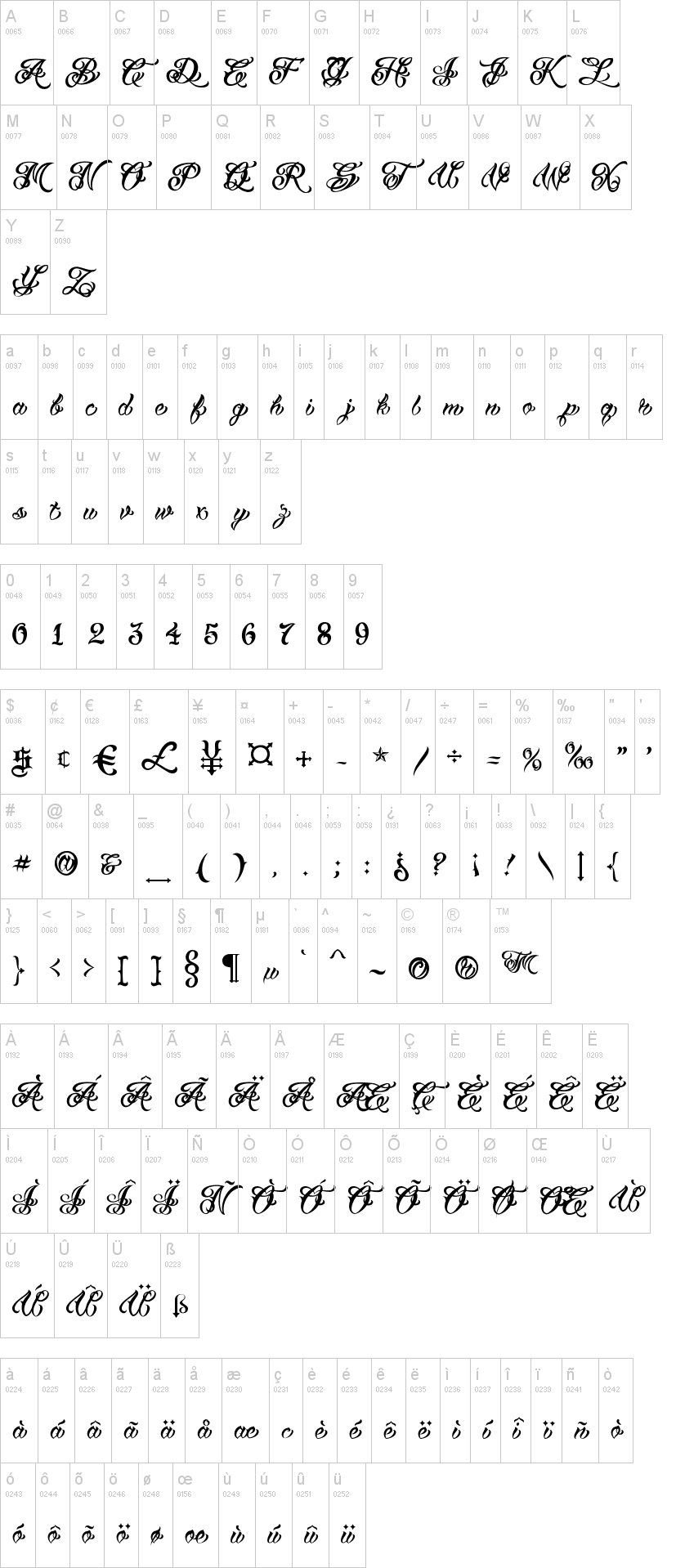
? VTC Tattoo Script Two 字体是一款纹身字体,它拥有清晰,粗犷,粗糙的艺术风格,可以满足现代纹身设计的需求。它具有传统手写样式的视觉效果,可以让您的设计更加有趣,而且还可以添加细节,以制作出个性化的纹身设计。此外,它还具有自定义字符和完整的拉丁字母表,可以满足您的所有需求。内容介绍
VTC Tattoo Script Two是一款非常不错的手写艺术字体,具有很好的视觉感,适合于文化类的宣传设计、商业类品牌的广告和产品包装设计以及个性化文字排版等较多场景。